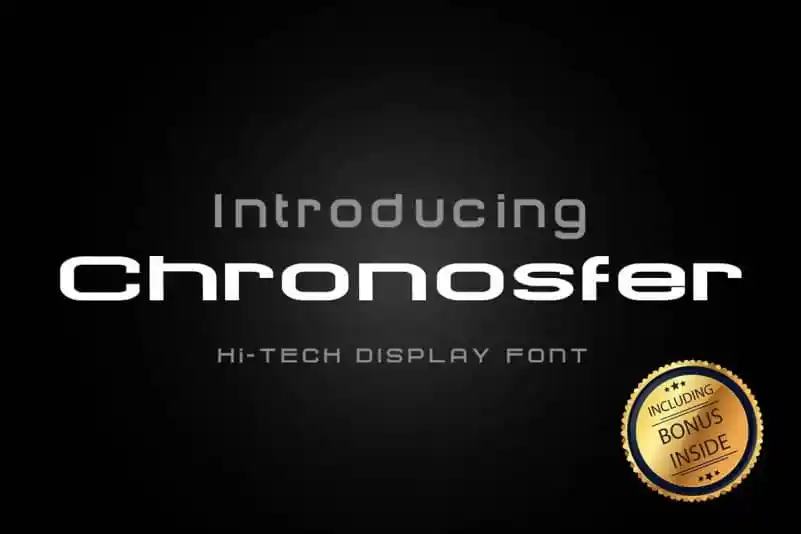
A Chronosfer Display Font é uma tipografia futurista com um impressiono moderno mas simples, tornando-a elegante e atraente quando combinada com outras fontes alternativas. Ela foi projetada por AnomaliDesign para celebrar o estilo original do letterpress e suas belas imperfeições. Suas formas estreitas e poderosas se adaptam perfeitamente para projetos de design forte, enquanto os texturas dão à fonte uma voz autêntica. Uma fonte que combina tecnologia moderna com um toque nostálgico, ideal para aplicativos digitais ou impressos que desejem adicionar um charme especial a seus materiais.